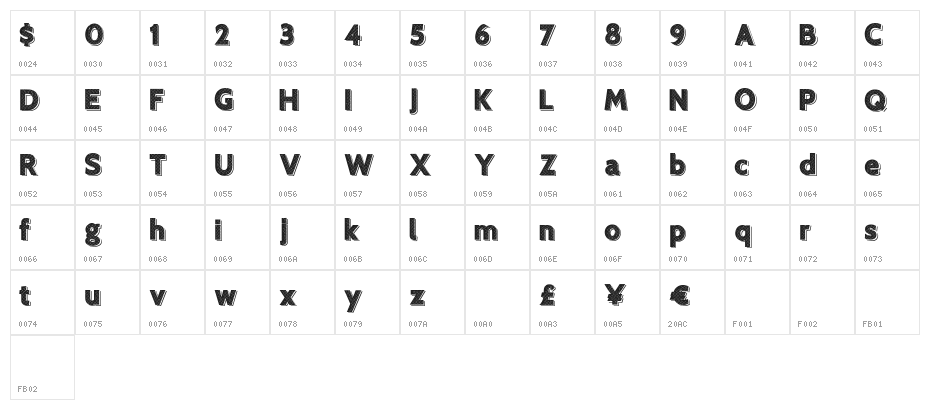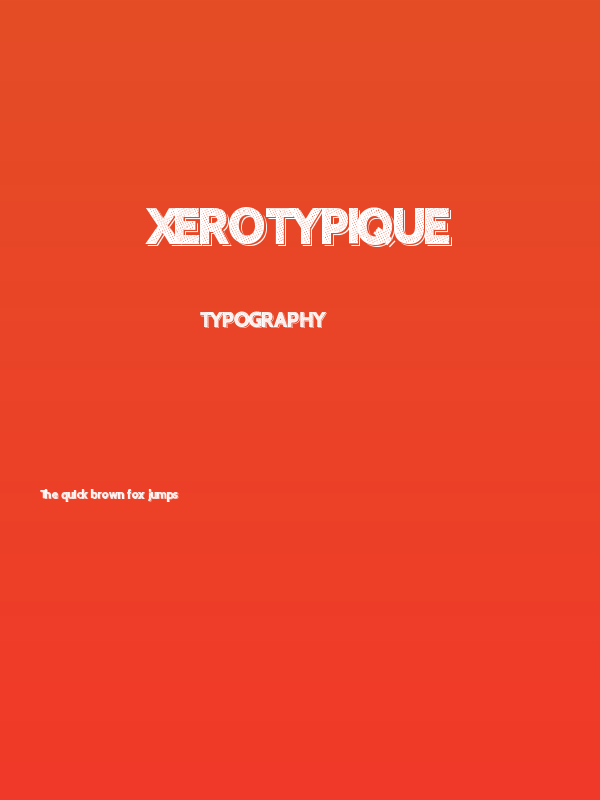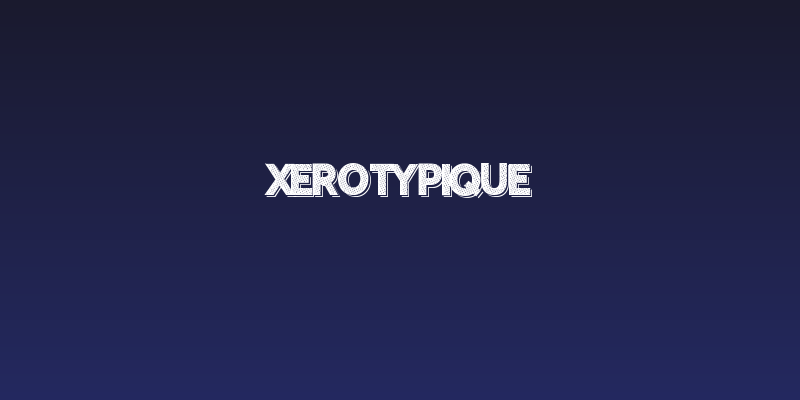
XeroTypique Font
| Progetti proposti | Ideal for posters, event flyers, children's book covers, and branding materials that require a playful and distinctive look. |